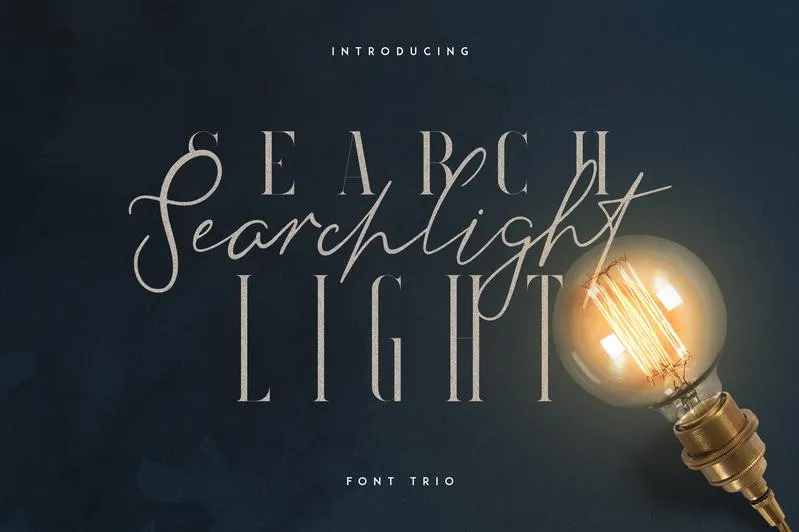
Searchlight Fonts – Free Demo – Download Grátis
Busca Luz é uma fonte que oferece uma trilogia elegante e vintage com três estilos de fontes, ligaturas e suporte multilíngue. Seu design atemporal combina sofisticação com um toque nostálgico, ideal para estilos variados como românticos ou modernos. Suas linhas elegantes e suas curvas perfeitas permitem que seja usada tanto em grandes proporções quanto em tamanhos menores, criando uma visão única de sua marca ou texto. Ideal para aplicativos digitais, impressões pessoais, designs gráficos, cartazes e tudo mais entre os quais você possa imaginar. Com suporte multilíngue, busca Luz é o ideal para designers que querem apresentar seus trabalhos em idiomas diferentes. É uma fonte extremamente versátil, perfeita para qualquer projeto, seja ele grande ou pequeno. Seja você um designer gráfico ou designer de arte digital, buscar Luz certamente irá adicionar um toque especial ao seu trabalho.